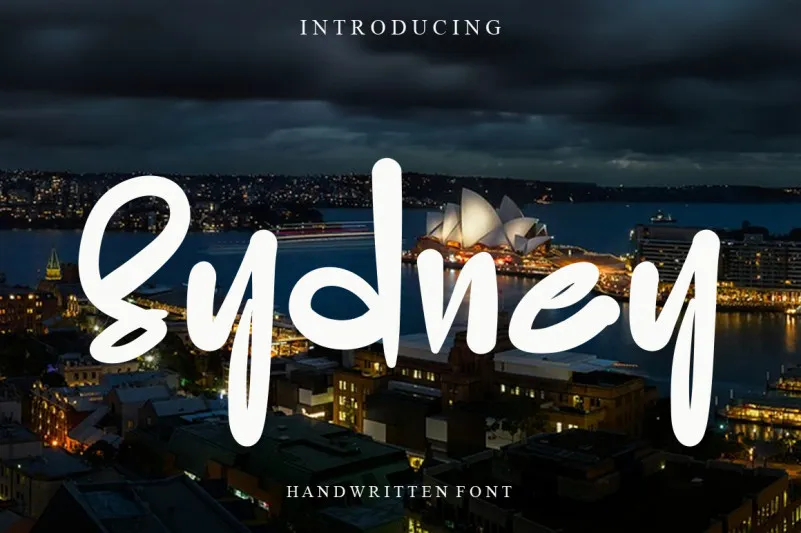
Sydney Font – Download Grátis
A fonte Sydney Font é uma escolha ideal para qualquer designer que busca adicionar um toque criativo a seus projetos. Embora seu design seja baseado em uma pintura texturizada e escrita à mão, ela não se limita apenas ao estilo. Esta font pode adaptar-se a vários assuntos, tornando-a um ativo valioso para o seu banco de fonts. Independentemente do tipo de projeto — seja uma marca empresarial, um design gráfico ou até mesmo um projeto editorial — Sydney Font tem potencial para melhorar e dar um tom único aos seus trabalhos. Com sua aparência delicada e fluida, essa font é perfeitamente adaptável à escrita, estilos, headlines e mais. Sua facilidade de uso faz dela uma excelente opção tanto para designers profissionais quanto para iniciantes que desejam adicionar um toque especial a seus trabalhos de design. Envolvente e natural como a própria Sydney, onde quer que você o use, Sydney Font certamente dará um charme único ao seu trabalho.